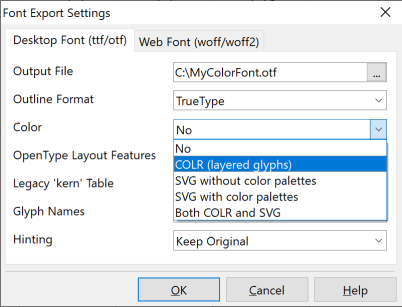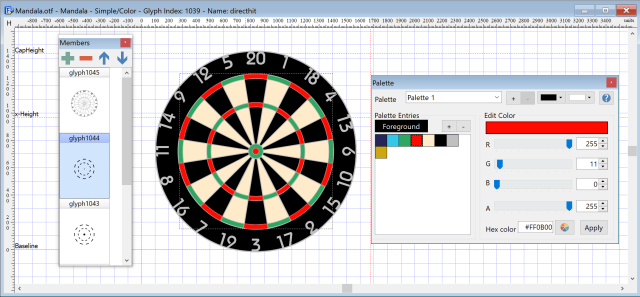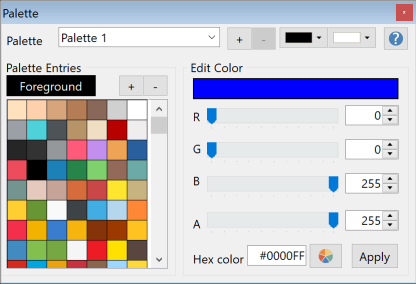
创建 OpenType 彩色字体
有两种可缩放的彩色字体扩展可以为您的 OpenType 字体增添色彩。本教程同时介绍 COLR 与 SVG 彩色支持的相关信息。
简介
最初,OpenType 字体格式不支持多色字体。这在 2013 年发生了变化,当时几家供应商推出了自己的解决方案,以满足操作系统、应用程序和网络浏览器对彩色表情符号的需求。我仍然记得参加 2013 年在阿姆斯特丹举行的 AtypI 会议,当时正式宣布将颜色添加到 OpenType 规范中。当时,对于采用哪种格式没有达成共识。决定是让所有主要参与者——Microsoft、Apple、Google、Mozilla 和 Adobe——各自提出自己的解决方案。
那时,我已经很清楚这会分散格局。事实上,在 2014 年,我在 High-Logic 论坛 上写道,这将导致竞争格式之间的一种"字体颜色战争"。十多年后,我们仍然在承受后果:OpenType 支持四种不同的颜色扩展。
• COLR/CPAL — Microsoft 的基于表的系统,具有分层字形和调色板。
• SVG — Mozilla 和 Adobe 的提案,嵌入 SVG 图形(可选地带有 CPAL)。
• CBDT/CBLC — Google 的基于位图的格式,用于 Chrome 中的彩色表情符号。
• sbix — Apple 的光栅图像格式(PNG、JPEG 等),用于 macOS、iOS 和 iPadOS。
在这些格式中,只有 COLR/CPAL 和 SVG 是可缩放的基于矢量的格式。FontCreator 支持这两种格式,使它们成为字体设计师最实用的选择。
COLR/CPAL
COLR 将彩色字形定义为单色轮廓的堆栈,每个轮廓都用调色板颜色绘制。因为它重用标准轮廓,所以它与可变字体无缝集成,并保持文件大小紧凑。
优势:轻量级、可缩放、可变字体友好。
限制:COLRv0 没有渐变;COLRv1(后来引入)添加了渐变、变换和合成。
COLR 颜色图层
在 FontCreator 中添加 COLR
要制作分层多色字形,您需要添加其他字形,然后为每个颜色成员定义颜色。与复合字形成员不同,您无法更改这些颜色成员的大小或位置。您需要确保单个字形都设计为适合彩色字形。
FontCreator 中的颜色模式
• 显示成员面板(Shift+F8)和调色板面板(Shift+F2)。
• 在字形编辑窗口中切换到颜色模式。
• 右键单击 → 添加(或单击成员面板中的添加图标)。
• 选择要包含的成员字形。
• 使用油漆桶工具分配调色板颜色。
实现说明
• 确保度量(前进宽度)在彩色字形和使用的字形成员之间匹配。
• 早期的 COLR 规范要求字形索引 1 为 .null 字形。这在当前规范中不再是要求。
SVG
SVG 扩展为每个字形嵌入一个 SVG 文档。它支持更丰富的图形,包括:
• 剪切路径、渐变、描边宽度。
• 不透明度和滤镜效果。
• 嵌入的光栅图像(通过 <image> 元素的 PNG/JPEG)。
SVG 彩色字体
只有受限的 SVG 1.1 子集在字体中有效:不允许 <a>、<text> 和 <font>,应避免动画或交互性。
最佳实践:
• 避免 <style> 和 viewBox,因为某些应用程序会错误地渲染它们。
• 优先使用矢量;光栅图像会增大文件大小并且缩放效果不佳。
在 FontCreator 中添加 SVG
FontCreator 不包括内置的 SVG 编辑器。您可以:
• 从 COLR 字形自动导出 SVG,或
• 从外部编辑器导入 SVG 图形。这提供了最大的灵活性,但可能很繁琐,因为坐标系通常需要调整,并且外部编辑器会产生臃肿的标记。
颜色调色板(CPAL)
CPAL 表定义可重用的颜色调色板:
• 前景色链接到用户选择的文本颜色。
• COLR:CPAL 是必需的;目前大多数应用程序仅使用第一个调色板,尽管 CSS font-palette 将在浏览器中带来更多控制。
• SVG:CPAL 是可选的,并未广泛实现。
网络浏览器彩色字体支持
网络浏览器 市场份额 COLR 支持 SVG 支持
Chrome 68% 是 –
Safari 17% 是 是
Edge(基于 Chromium) 5% 是 –
Firefox 3% 是 是
Samsung Internet 2% 是 –
Opera 2% 是 –
Internet Explorer <1% 是 –
注意: 市场份额指示截至 2025 年 7 月。Edge 从 2017 年开始支持 SVG,但自 2020 年转移到 Chromium 后不再支持。Chromium 项目没有计划添加 OT-SVG 支持。
软件彩色字体支持
软件 COLR/CPAL 支持 SVG 支持
Adobe Illustrator 是(v29.3 / 2025+) 是(CC 2018+)
Adobe InDesign – 是(CC 2019+)
Adobe Photoshop 是(2025+) 是(CC 2017+)
QuarkXPress 是(2018+,包括 COLRv1) 是(2018+)
Affinity Designer 是 –
Affinity Publisher 是 –
Sketch(macOS) COLRv0 是(macOS 10.14+)
Microsoft Word(Windows 10/11) 是 是
Microsoft PowerPoint(Windows 10/11) 是 是
Microsoft Excel(Windows 10/11) 是 是
LibreOffice 是(6.3+) 部分
paint.net(Windows) 是 –
CorelDRAW Graphics Suite – 是
Figma – –
Procreate(iPad) COLRv0 是
Adobe After Effects / Premiere Pro – 是(2025+)
Inkscape – 部分
Scribus 部分 –
GIMP 部分 –
注意: COLR/CPAL 是基于轮廓的颜色格式(v0 = 分层字形;v1 添加渐变、变换和合成)。没有嵌入位图。大多数使用 CoreText 的原生 macOS 应用程序支持 COLRv0。CoreText 尚不支持 COLRv1。OpenType-SVG 存储 SVG 文档,可以包括矢量形状和嵌入的光栅图像(例如,通过 SVG <image> 元素的 PNG/JPEG),加上渐变/不透明度/滤镜。OpenType 使用受限的 SVG 1.1;功能支持因应用程序/操作系统而异。macOS 通常需要 10.14+ 才能渲染 SVG 字体。大型光栅内容可能会增加字体大小。
我应该使用哪种颜色扩展?
• 对于网络,COLR 是明确的选择:紧凑、可靠、可变字体兼容,并且在浏览器中普遍支持。
• 对于桌面出版,这取决于情况。虽然越来越多的软件支持 COLR,但有些仍然只识别 SVG。最好提供两种格式,以便最终用户可以决定使用哪一种。
指导:
• 如果渐变是不必要的,请优先使用 COLR。然后您可以导出为 SVG 以确保兼容性,确保两种格式共享相同的轮廓。
• 如果渐变或复杂渲染是必不可少的,请尽可能使用 COLRv1,或回退到 SVG。
• 避免在一个字体中同时打包 COLR 和 SVG;虽然技术上允许,但这会使文件膨胀并可能导致渲染不一致。